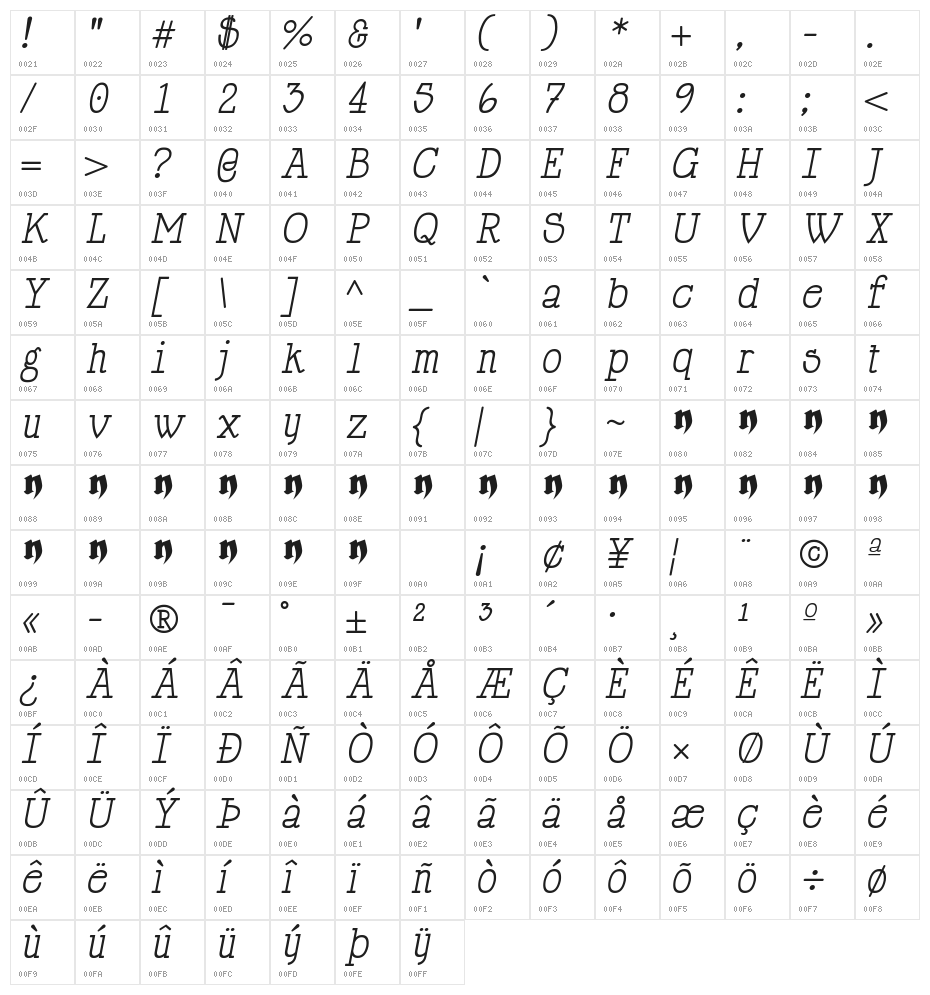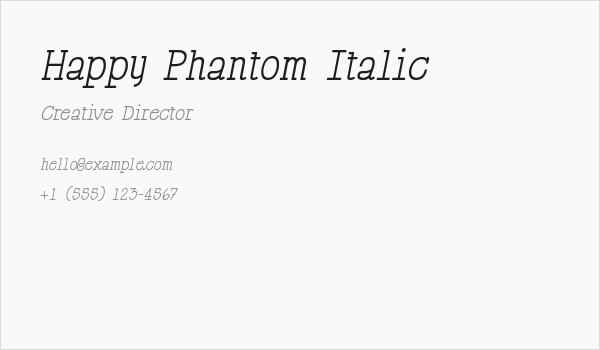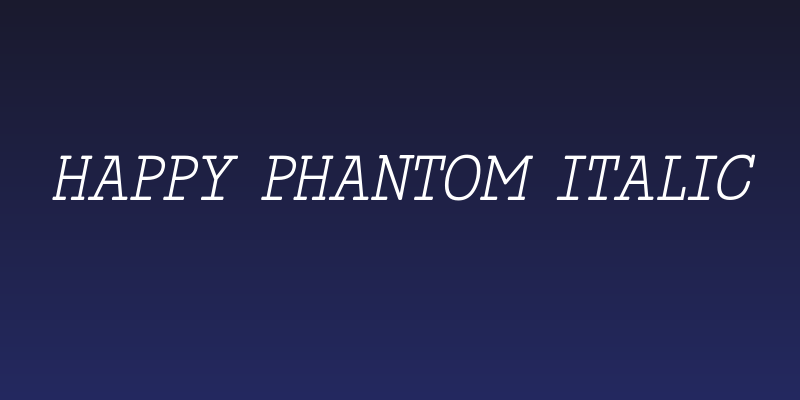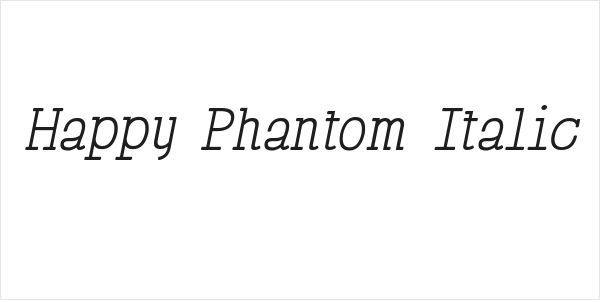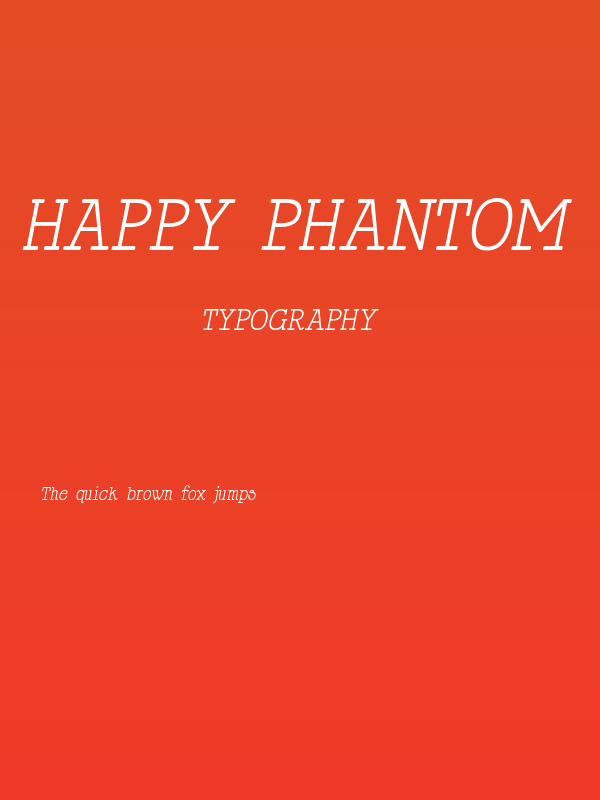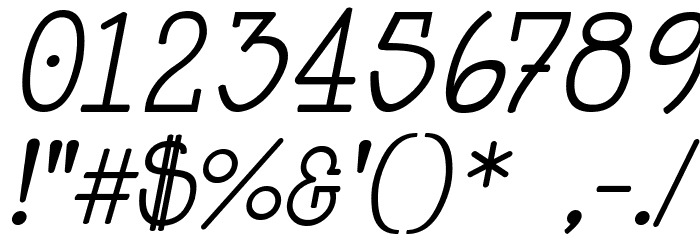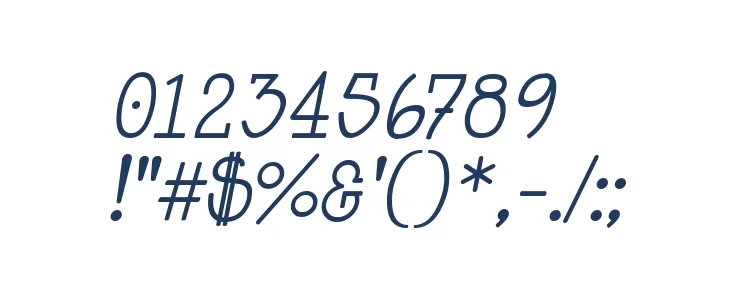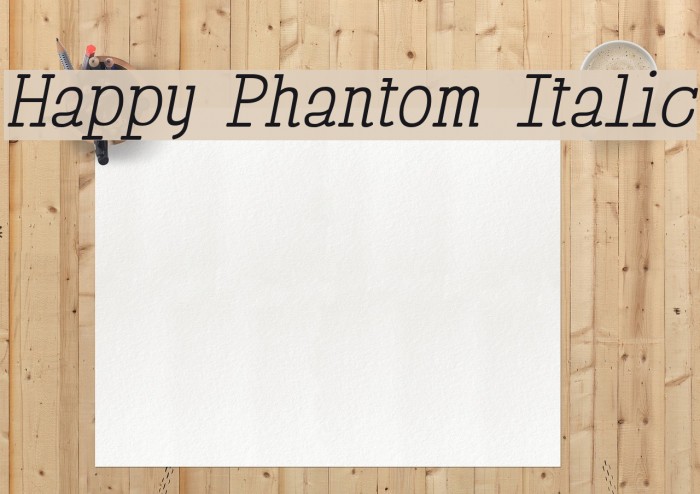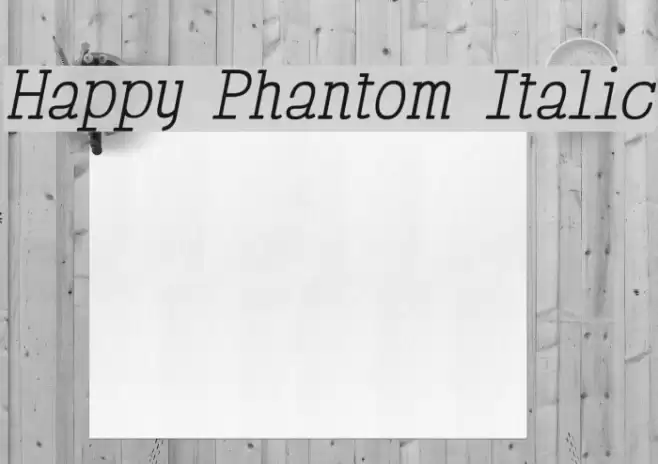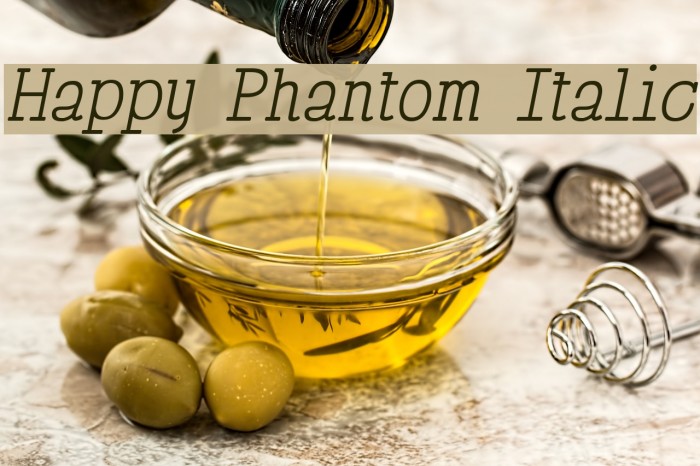
Happy Phantom Italic Font
✎ Serif
| Estilo general | Classic |
| Caso de uso | Headlines, Body text, Logos |
| Proyectos propuestos | Ideal for editorial design, book covers, formal invitations, and branding materials that require a touch of elegance. |